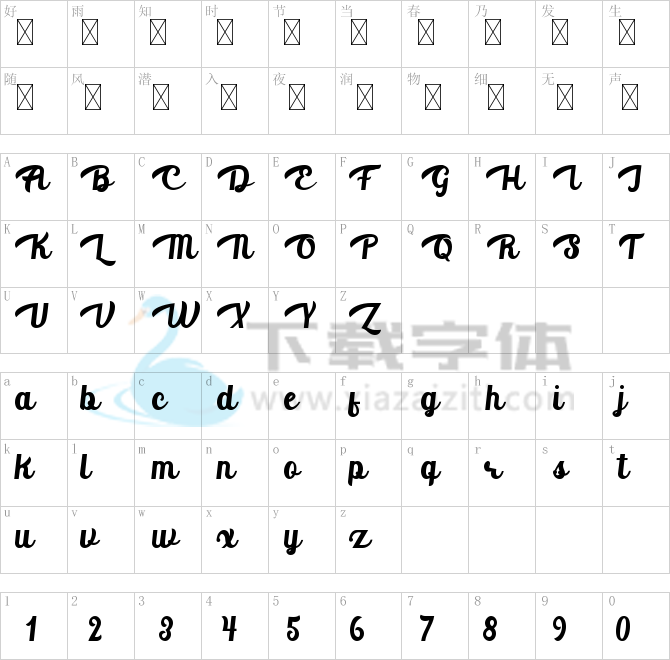
Aventurina.ttf字体下载,这款字体结构工整、笔画清晰,兼顾美观与易读性,适用于标题、正文、海报、包装、LOGO 等多种场景。字形优雅稳定,风格百搭耐看,适配日常排版与创意设计,让文字呈现更舒适、更具质感。Aventurina.ttf字体下载一笔一画,皆是细节,以均衡的比例、流畅的线条打造舒适视觉体验,字形端正大气,风格简约现代。无论是商业设计、品牌宣传还是日常排版,都能轻松驾驭,让文字更有格调与力量。Aventurina.ttf字体下载字体下载。
• 字体名称:Aventurina